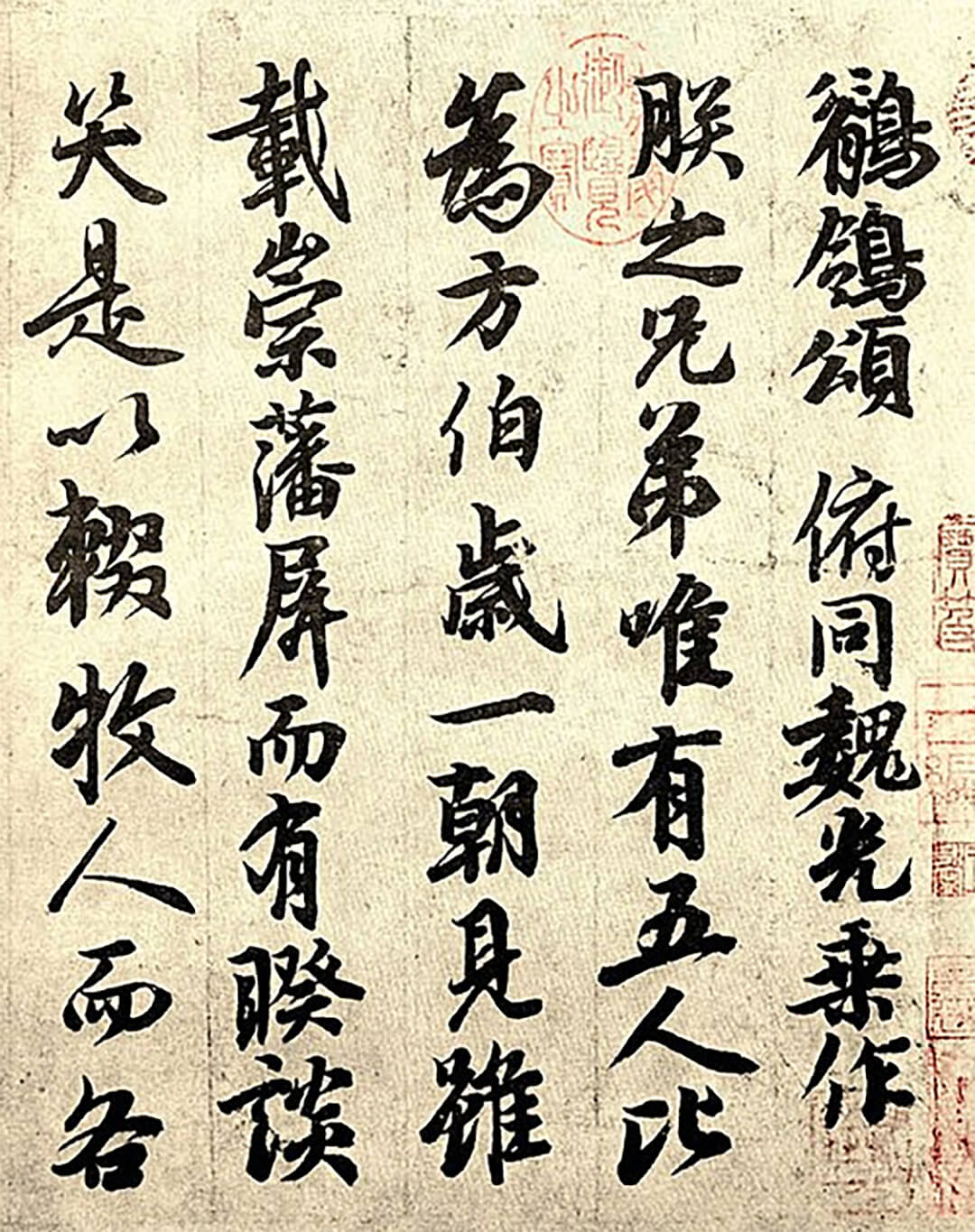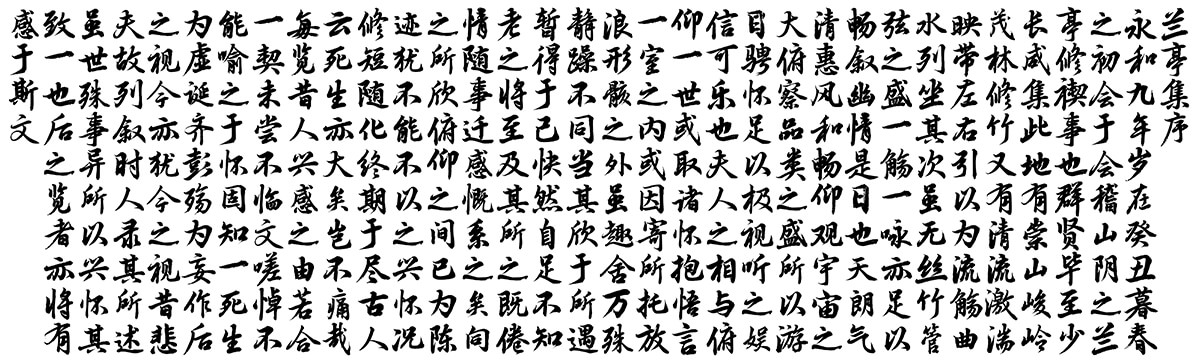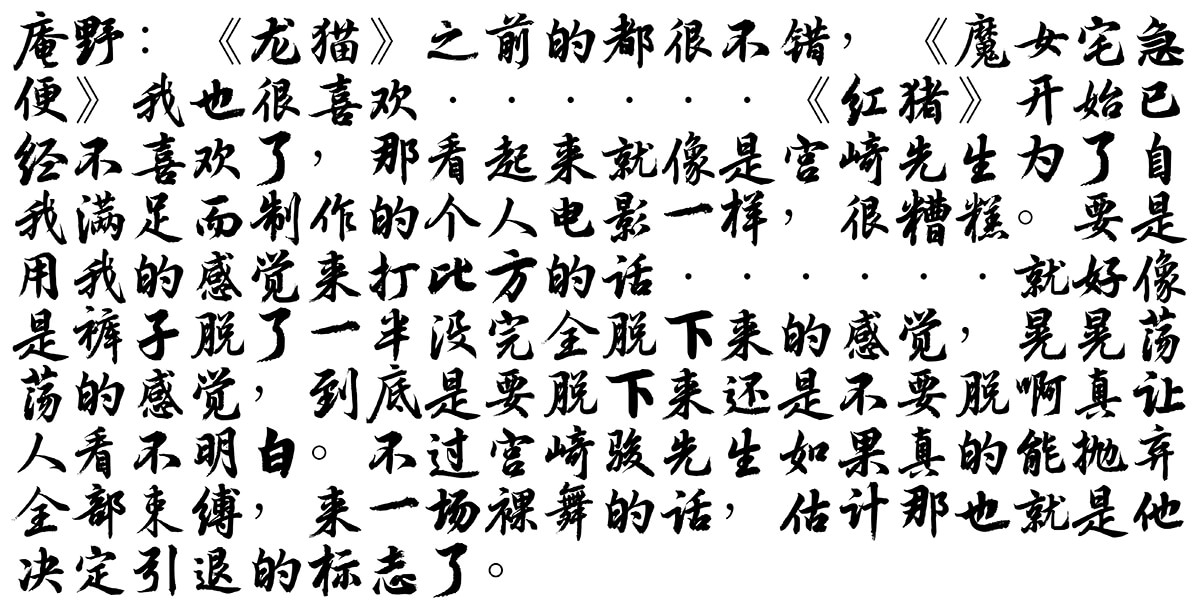
玄宗体(XuanZongTi)是一款以唐玄宗李隆基行书真迹《鹡鸰颂》为原型、借助 zi2zi-Ji 生成的免费商用书法字体。
《鹡鸰颂》的原始样本页
《鹡鸰颂》创作于唐玄宗中年时期,全卷40行、337字,单字大小约4厘米,以笔法遒劲、结体丰丽著称,展现了盛唐书法的雄浑气度。玄宗体则是在其基础上通过现代字体生成技术,字符经矢量化描边后编译为OpenType格式,既保留了保留传统韵味,又兼顾了现代屏幕的阅读需求。
玄宗体覆盖 GB2312 字符集(含6763个汉字),支持简体和部分繁体中文,比较适合历史文化、典雅、国风类的设计场景。